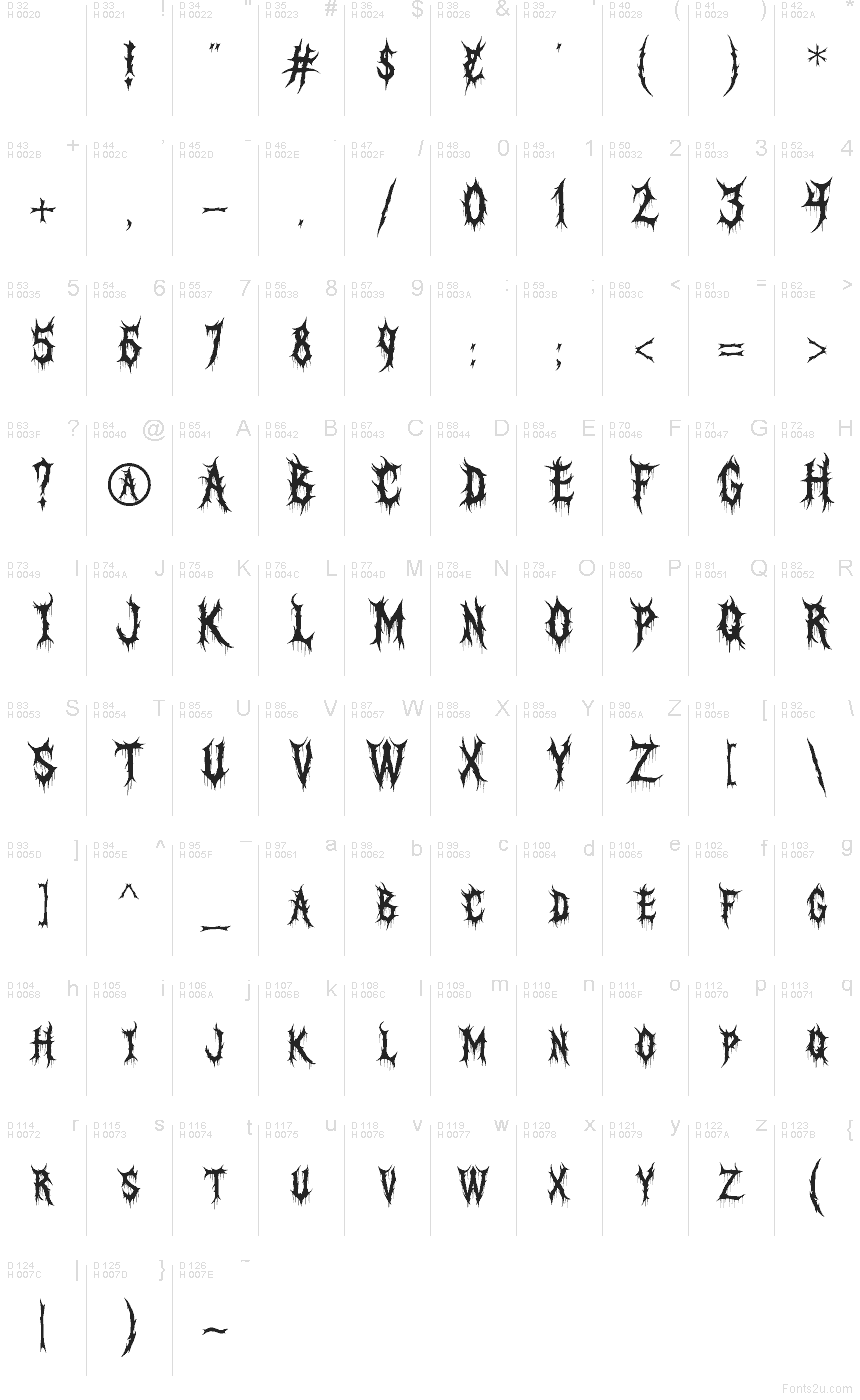
Písmo Darkhorn od studia Masyafi Studio je bezplatný gotický font s rozeklanými písmeny připomínajícími drápy a ostrými vertikálními řezy, které celé sadě dodávají drsný, potrhaný vzhled. Tahy se lámou do špičatých hrotů a tenkých kapek, takže výsledný dojem je spíše vytesaný než psaný.
Darkhorn skvěle funguje na hororových plakátech, grafice metalových kapel, titulech her, tetování a halloweenském designu, protože jeho roztříštěné tvary nesou drsný, rituální nádech. Toto bezplatné písmo se také hodí pro výrazné nadpisy, pozvánky na akce a temná loga všude tam, kde design vyžaduje písmena, která vypadají poškozeně, ostře a záměrně nezkrotně.